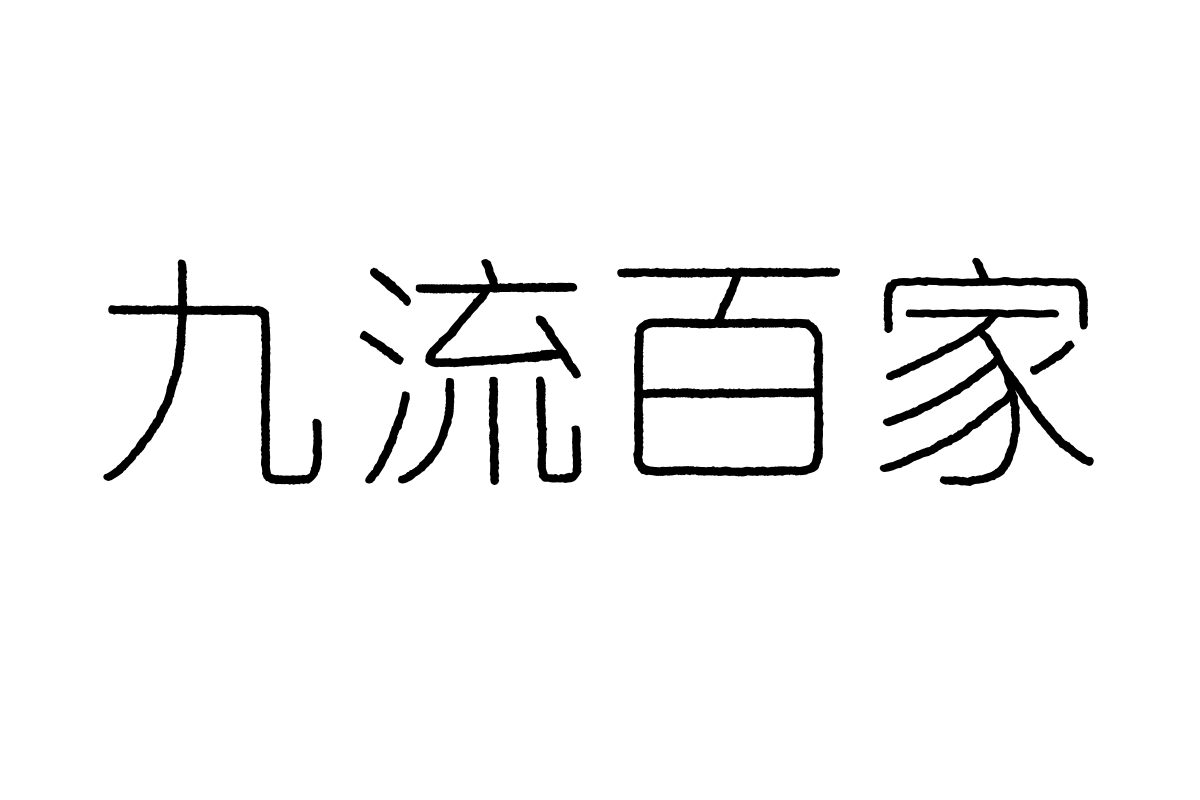
龚帆魅力纤细圆字体是一种具有独特美感的字体,它的特点是线条纤细、圆润。这种字体适合用于需要强调细节和柔美效果的设计场景,如平面设计、网页设计、UI设计等。龚帆魅力纤细圆字体的特点在于其线条的细腻和圆润,给人一种优雅、柔和的感觉。同时,它的结构紧凑,笔画连贯,使得整个字体看起来更加和谐、统一。
在设计中,龚帆魅力纤细圆字体可以用于标题、文字、图标等元素,能够很好地传达出设计的主题和情感。例如,在平面设计中,可以使用这种字体来制作广告、海报、宣传册等;在网页设计中,可以用来制作网站的标题、按钮、导航栏等;在UI设计中,可以用来制作应用程序的图标、按钮、文字等。
总之,龚帆魅力纤细圆字体以其独特的美感和实用性,被广泛应用于各种设计场景中,为设计作品增添了更多的艺术感和表现力。